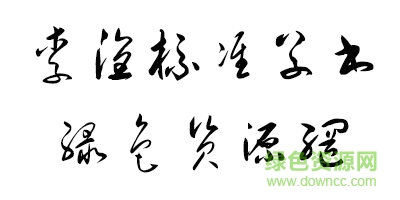
鐘齊李洤標(biāo)準(zhǔn)草書(shū)符號(hào)
李洤標(biāo)準(zhǔn)草書(shū)字體是一款非常漂亮的草書(shū)書(shū)法字體,這款字體筆畫(huà)行云流水,字形俊逸灑脫,整體效果非常出色,喜歡這款字體的朋友歡迎來(lái)綠色資源網(wǎng)下載使用!
李洤標(biāo)準(zhǔn)草書(shū)字體效果展示
李洤標(biāo)準(zhǔn)草書(shū)字體